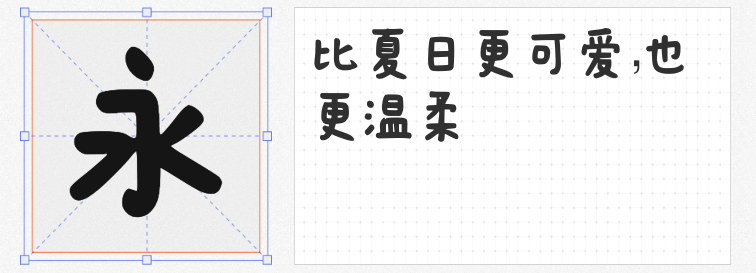
在音乐专辑、文创周边等需要传递温暖与趣味的场景中,字体的选择往往能成为视觉氛围的“点睛之笔”。以下四款免费可商用的创意字体,以独特的造型语言诠释可爱美学,兼顾个性表达与实用适配性,助你轻松打造令人过目难忘的专辑设计!
这款字体以法棍面包为灵感原型,笔画纤细如面包胚的轻盈质感,却通过规律性局部加粗强化视觉焦点,曲线与折角的处理既保留了宋体的优雅骨架,又融入了手写体的俏皮呼吸感。其“可爱不粗苯”的气质,尤其适合清新民谣、独立音乐等专辑封面,用克制的甜度传递纯粹的艺术温度。
也字工厂小石头体以软笔笔触模拟像素颗粒的圆润感,字形如弹力橡皮糖般饱满,粗细对比强烈的笔画却暗藏洒脱张力。这种“柔软与力量”的矛盾美学,既能驾驭儿童音乐、动漫OST等童趣主题,也能为电子乐、流行专辑注入年轻化的叛逆感,通过自由随性的书写风格,让文字成为跳动的音符符号。
基于日本「解星计划」与中文传承字形检校表开发,小狼天穹在保留宋体规整骨架的同时,通过繁简体字与注音符号的完整覆盖,赋予字体“严谨与可爱并存”的独特气质。其略带复古感的字形结构,适合用于爵士乐、古典跨界等专辑设计,用学术般的精致感平衡艺术的实验性。
由AI算法生成的字体家AI造字春风体,以夸张的圆弧笔画与动态倾斜打破传统字体的静态秩序,卡通化笔触自带萌系滤镜。无论是电子音乐、游戏原声等科技感主题,还是节日限定专辑的欢快氛围,这款字体都能通过赛博朋克的视觉张力,让文字成为连接虚拟与现实的趣味接口。
可爱风字体并非“甜腻”的代名词,尝试通过低饱和度配色、几何图形穿插或动态效果,让文字与专辑主题形成张力对话。这四款免费字体已为你备好创意起点,快用它们书写属于你的音乐故事吧!